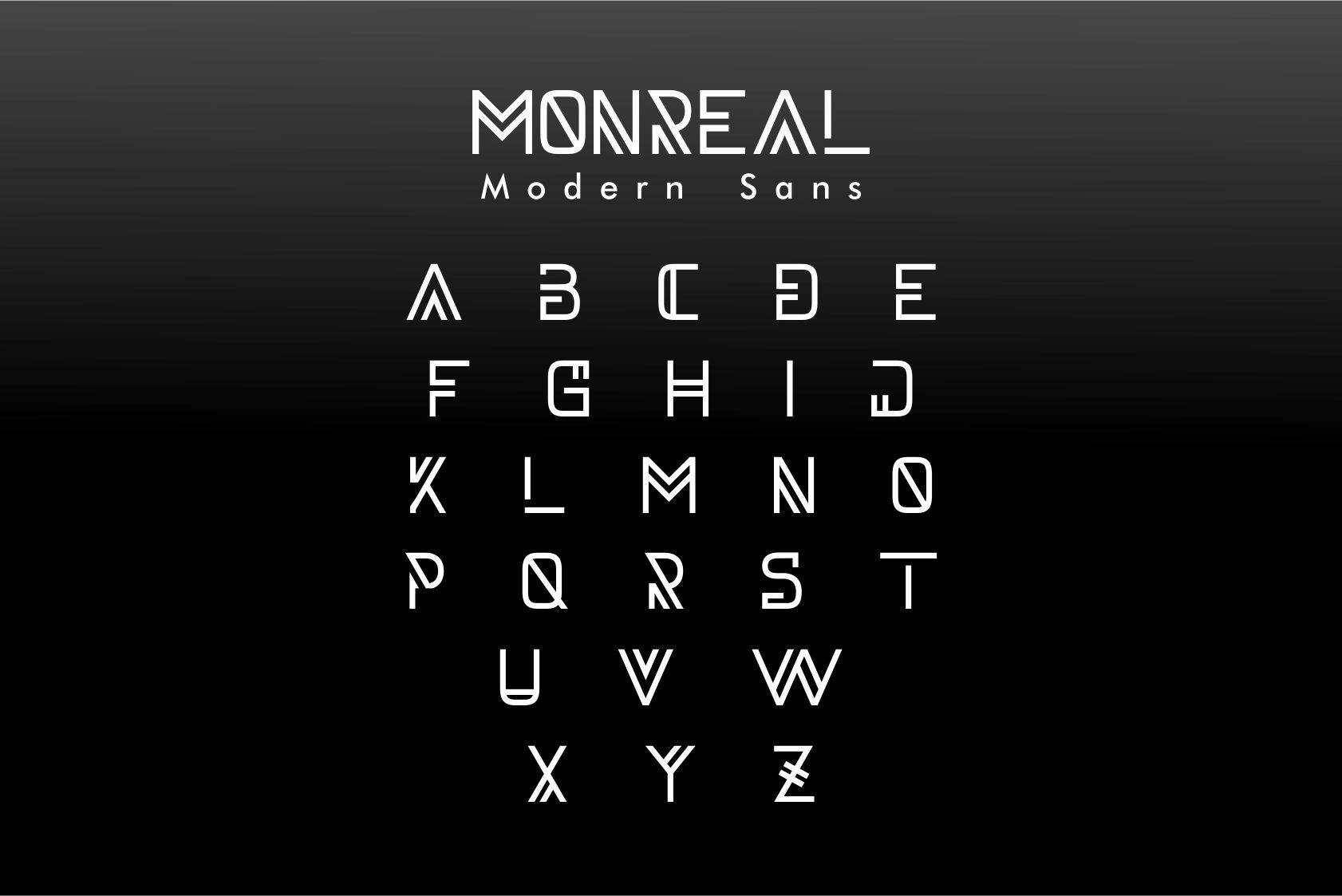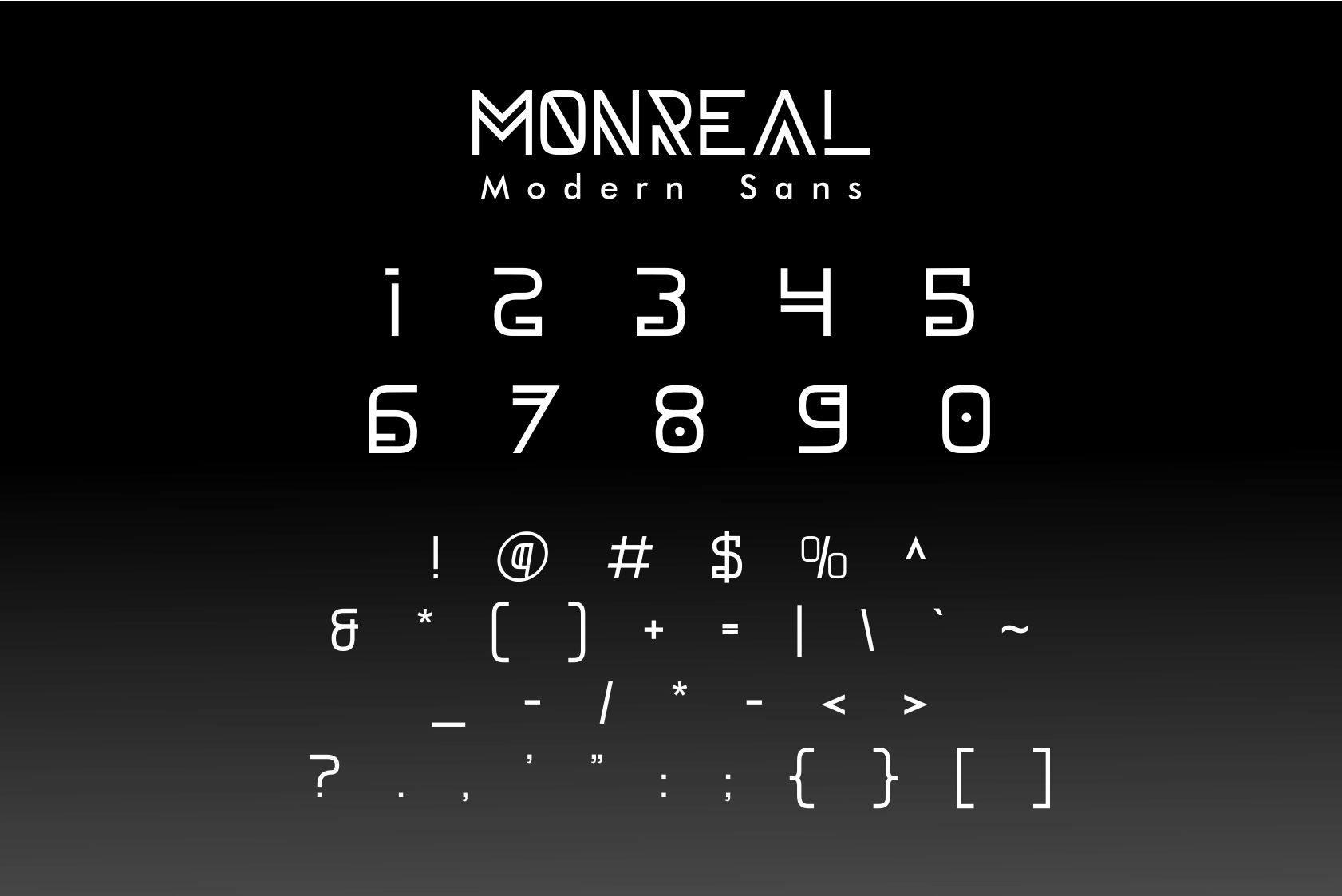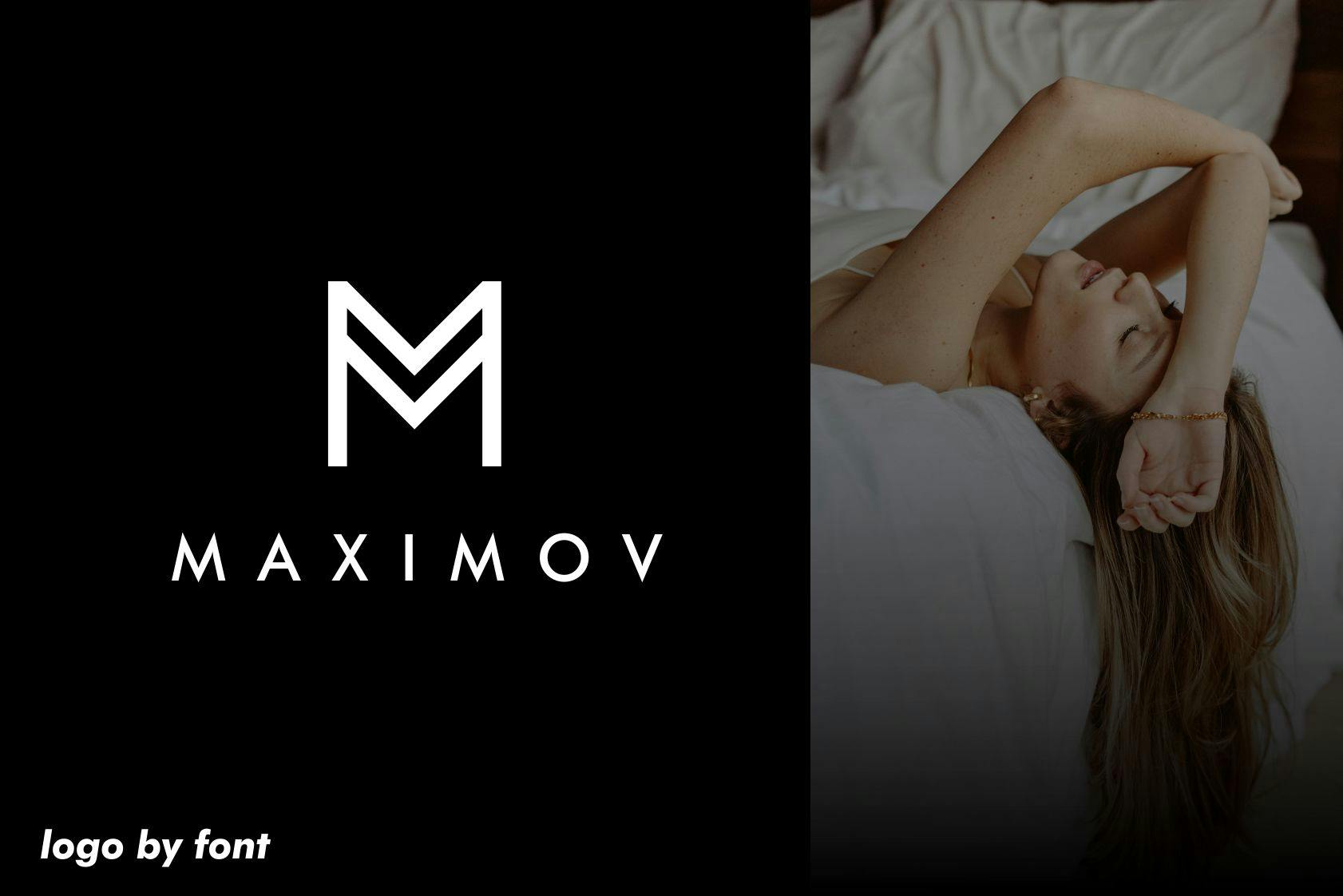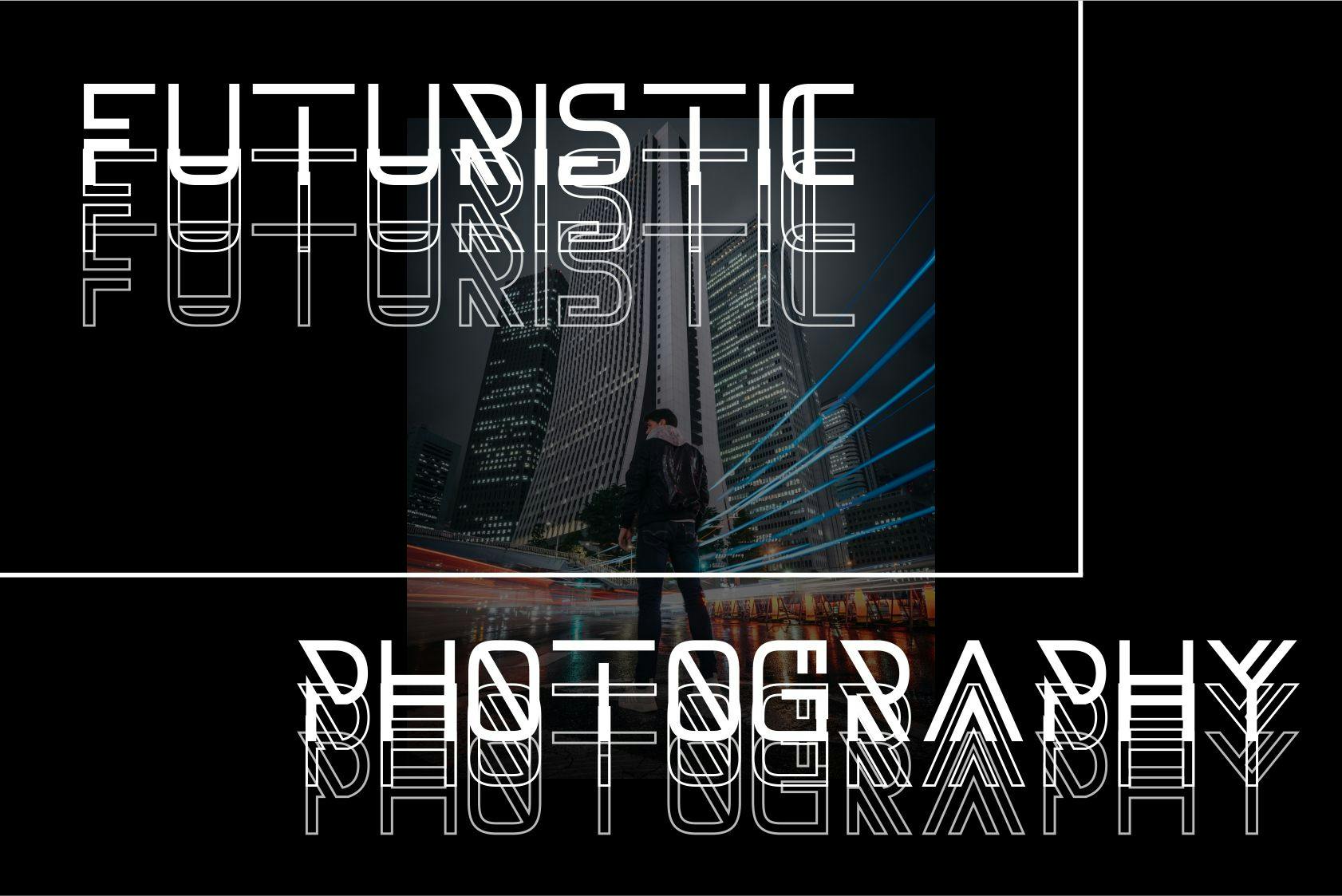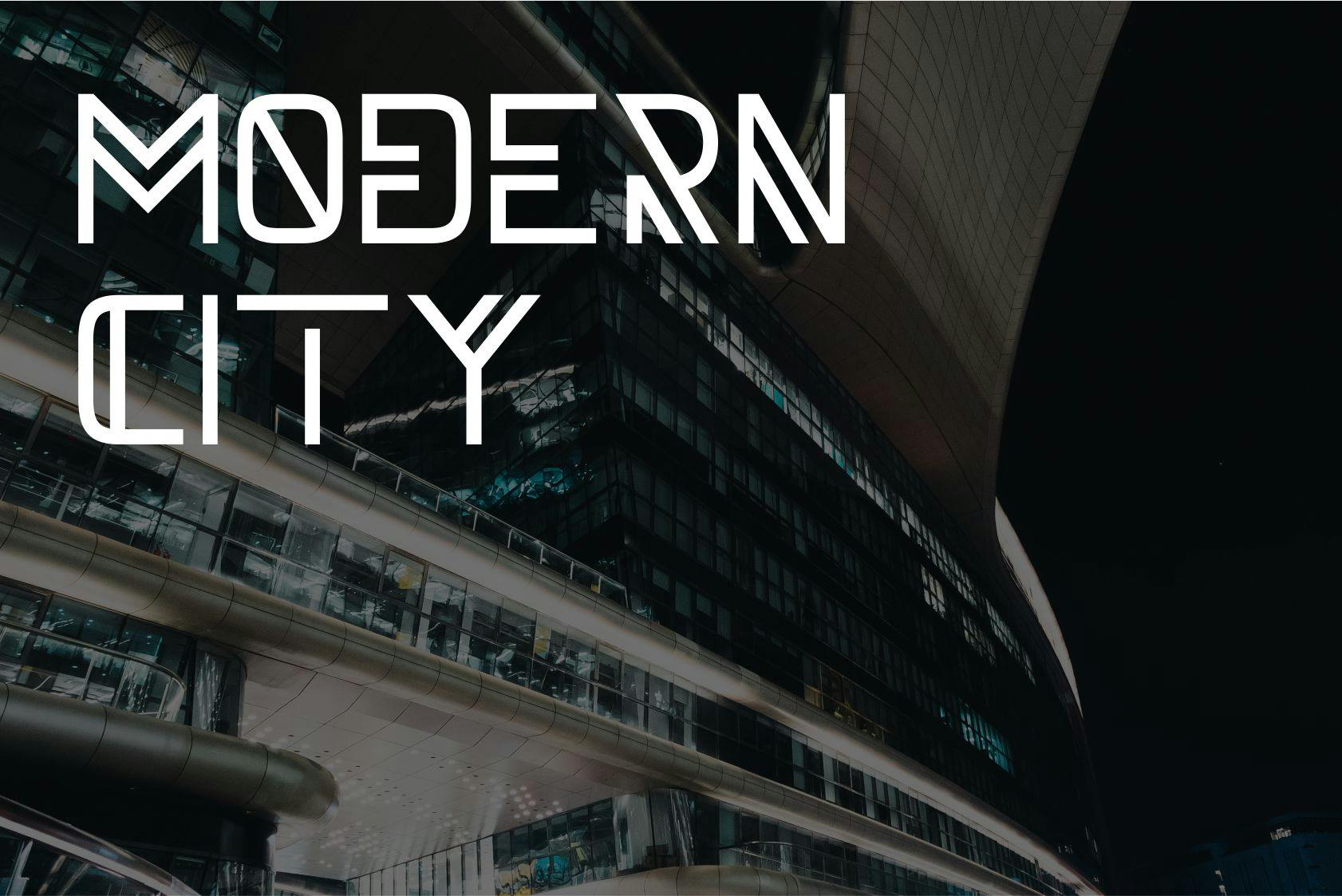
فونت Monreal شامل حروف بزرگ، اعداد و دامنه وسیعی از نشانهگذاریها میباشد. این فونت بدون سریف با سبک مدرن، برای طراحی پوستر، طراحی وب، برندینگ، иллюстрации، نشانها و سایر پروژهها ایجاد شده است.